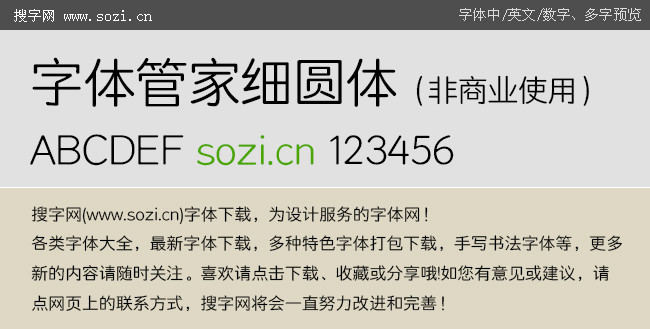
字體管家細(xì)圓體(非商業(yè)使用)
搜字網(wǎng)給大家提供一款字體管家細(xì)圓體(非商業(yè)使用)中文字體下載,字體管家細(xì)圓體(非商業(yè)使用)是一款字形清秀的中文字體,該字體結(jié)構(gòu)優(yōu)美,識(shí)別性好,適合海報(bào)設(shè)計(jì)、包裝畫冊(cè)等宣傳廣告等應(yīng)用(此字體為個(gè)人非商用版,商用可以聯(lián)系QQ:1006760504)。